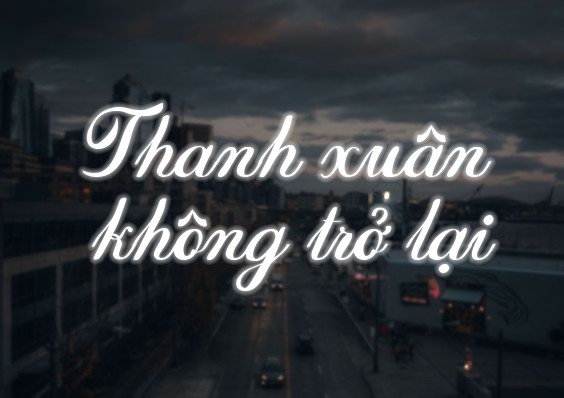
Giới thiệu về Font việt hóa MJ Fuego
Trong thế giới đồ họa hiện đại, việc tìm kiếm một bộ Font Chữ vừa mang nét cá tính riêng biệt vừa hỗ trợ đầy đủ bảng mã tiếng Việt là điều vô cùng quan trọng. Font việt hóa MJ Fuego nổi lên như một lựa chọn hàng đầu cho những ai yêu thích phong cách viết tay phóng khoáng và tự nhiên. Bộ font này không chỉ giữ trọn vẹn tinh thần sáng tạo của tác giả gốc mà còn được tinh chỉnh tỉ mỉ về dấu câu, giúp các nhà thiết kế Việt Nam dễ dàng ứng dụng vào nhiều dự án khác nhau từ học đường đến truyền thông chuyên nghiệp.
Đặc điểm nổi bật của Font việt hóa MJ Fuego
Phong cách thiết kế thủ công tinh tế
Điểm thu hút nhất của Font việt hóa MJ Fuego chính là những đường nét uốn lượn đầy cảm xúc. Mỗi ký tự được mô phỏng theo nét bút thật, tạo cảm giác gần gũi và chân thực. Điều này giúp bài thuyết trình hoặc thiệp mời của học sinh trở nên sinh động hơn bao giờ hết.
Khả năng ứng dụng linh hoạt
Dù bạn đang thiết kế bìa sách, poster sự kiện hay làm nội dung cho mạng xã hội, font chữ này đều đáp ứng tốt. Sự kết hợp giữa nét thanh và nét đậm tạo nên sự cân bằng thị giác hoàn hảo, giúp thông điệp của bạn dễ dàng chạm đến trái tim người xem.
Lợi ích khi sử dụng Font việt hóa MJ Fuego trong giáo dục